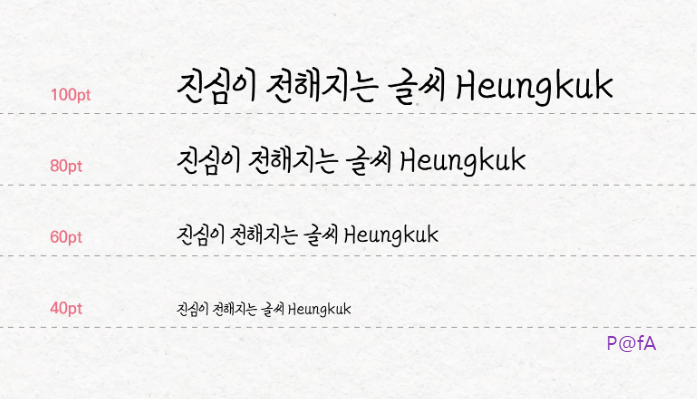
누구나 개인적인 용도뿐만 아니라 상업적인 용도에도 무료로 사용할 수 있도록 제공하는 무료 글꼴인 심경하체를 소개한다. 심경하체는 흥국생명이 주최한 2021년 제1회 디지털 손글씨 공모전에서 최우수작으로 선정된 글꼴 중 하나이다. 이때 선정된 글꼴은 심경하체 이외에 이서윤체와 전화선체도 있는데, 다음에서 제시하는 순서대로 따라 하면 심경하체를 무료로 다운로드해서 사용할 수 있다.
위의 이미지에서 보듯이 심경하체는 전형적인 명조체 스타일에 초성의 자음이 선명한 도드라지는 형태의 손글씨 서체이다.
위에서 보듯이 심경하체는 받침으로 사용된 ㄴ과 ㄹ에서 보듯이 손글씨 특유의 유연한 꺾임과 초성으로 사용된 자음에서도 전형적인 손글씨 모양을 확인할 수 있다. 또한 아래에 설치 화면에서 확인할 수 있듯이 모음이 대부분 꺾임으로 시작하고 자음 중 ㅂ, ㅌ, ㅍ이 다소 독특한 형태로 제작된 글꼴이다. 이러한 심경하체를 컴퓨터에 설치하는 방법은 매우 간단하다. 설치를 원하는 해당 파일을 누른 후에 나오는 팝업에서 설치 버튼을 눌러주면 된다.
앞에서 언급했듯이 해당 심경하체는 손글씨 공모전에서 수상한 서체를 폰트로 제작했기에 직접 손으로 쓴 든 굴림 형태가 두드러진 손글씨 서체이므로 형식과 격식을 요구하는 문서에서는 가급적 사용을 자제할 필요가 있다. 더불어 해당 심경하체 폰트는 IOS용 모바일에서 공식적으로 사용 가능한데, 모바일용 흥국생명 디지털 손글씨 공모전 사이트에서 IOS용 폰트 다운로드 버튼을 누르면 자동으로 아래에 같이 앱스토어로 연결된다.